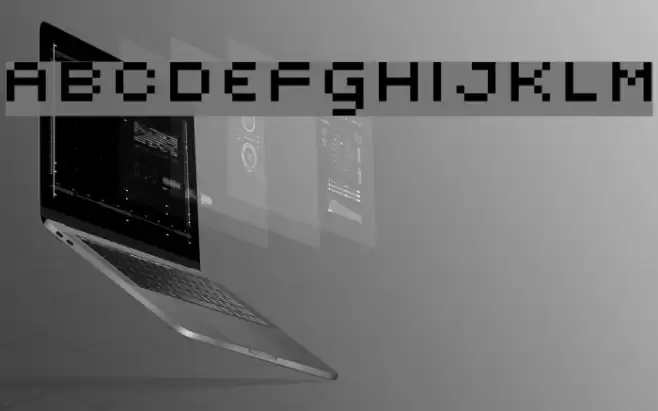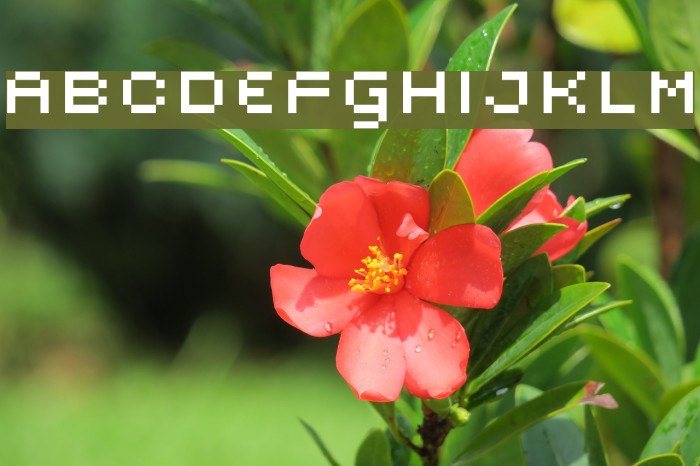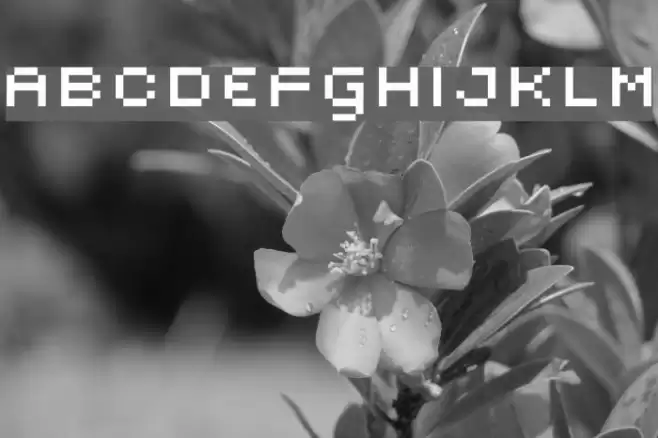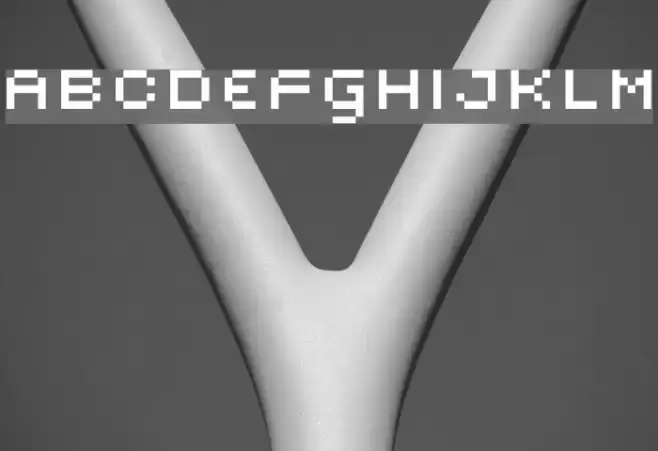
Subatomic Screen Font
✎ Pixel
| Gesamtstil | Retro, Digital |
| Anwendungsfall | Logos, Headlines, Posters |
| Vorgeschlagene Projekte | Ideal for retro video game designs, digital-themed posters, tech-related branding, and any project seeking a nostalgic digital look. |